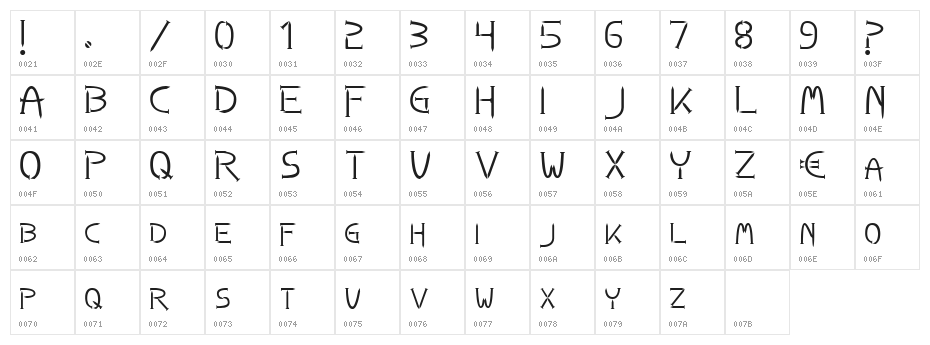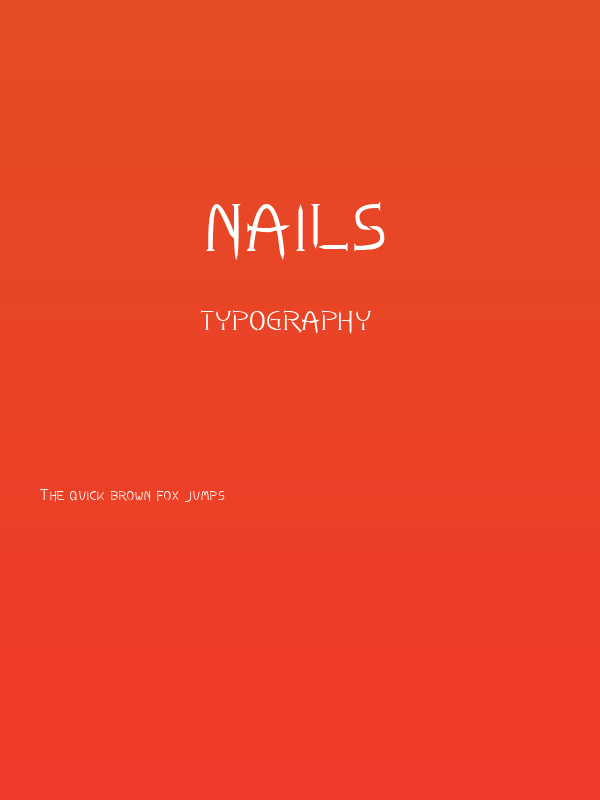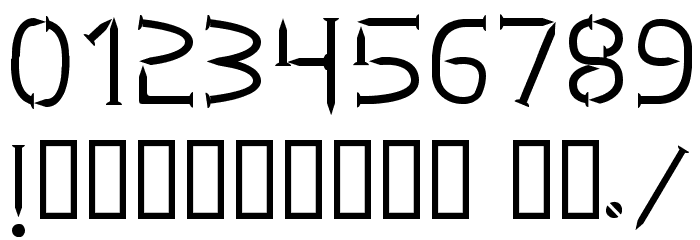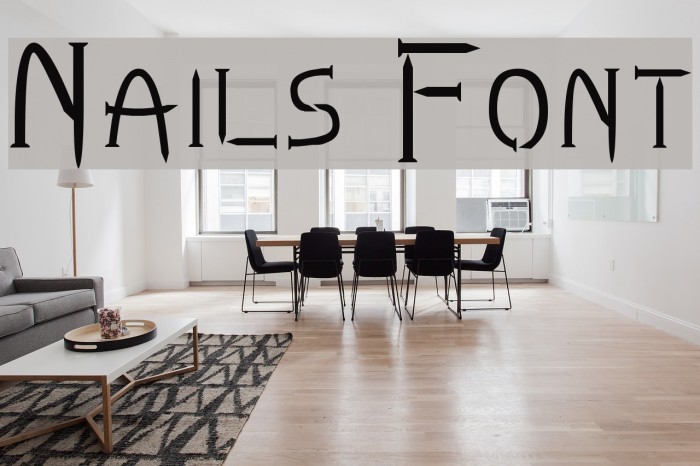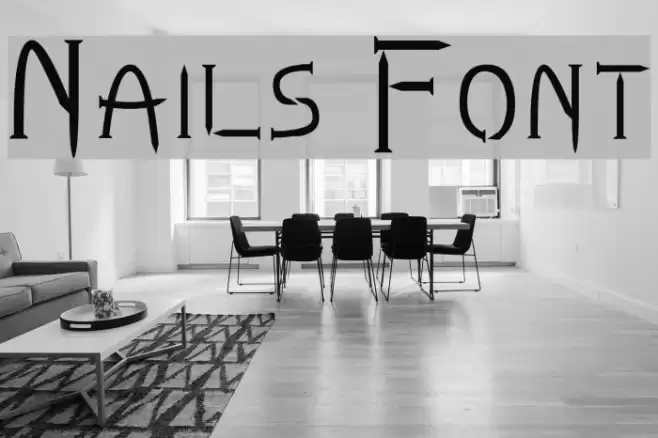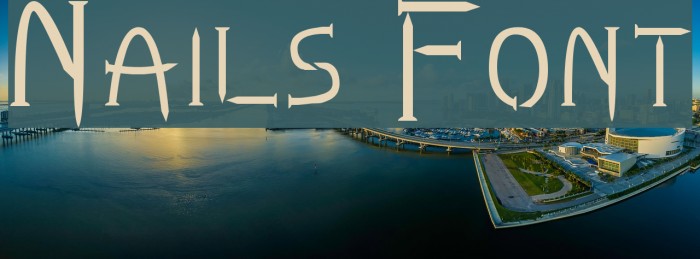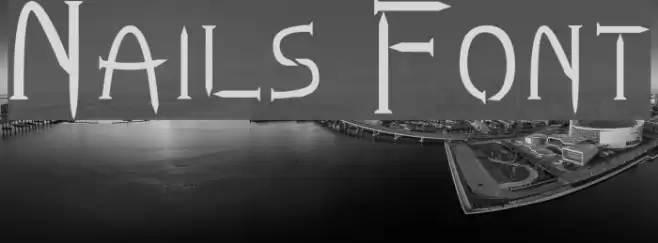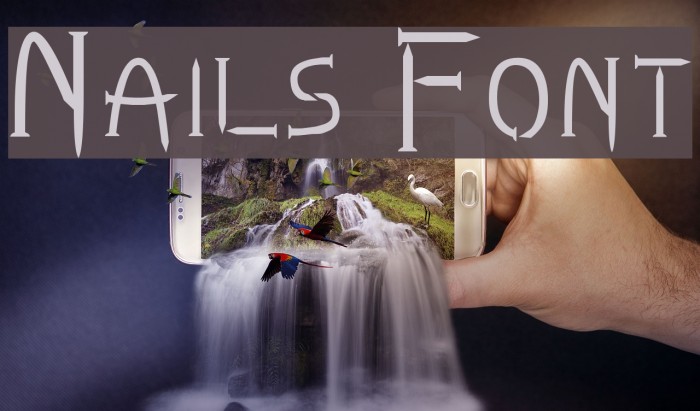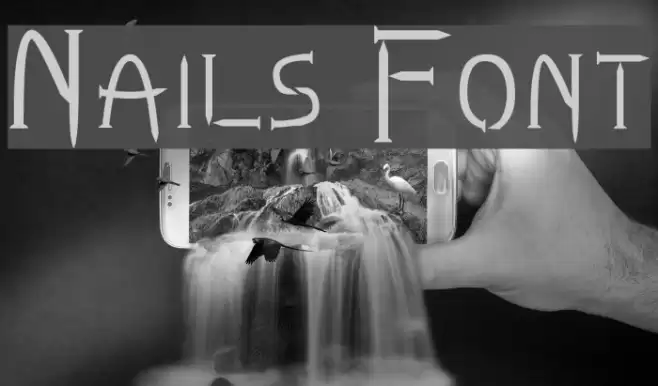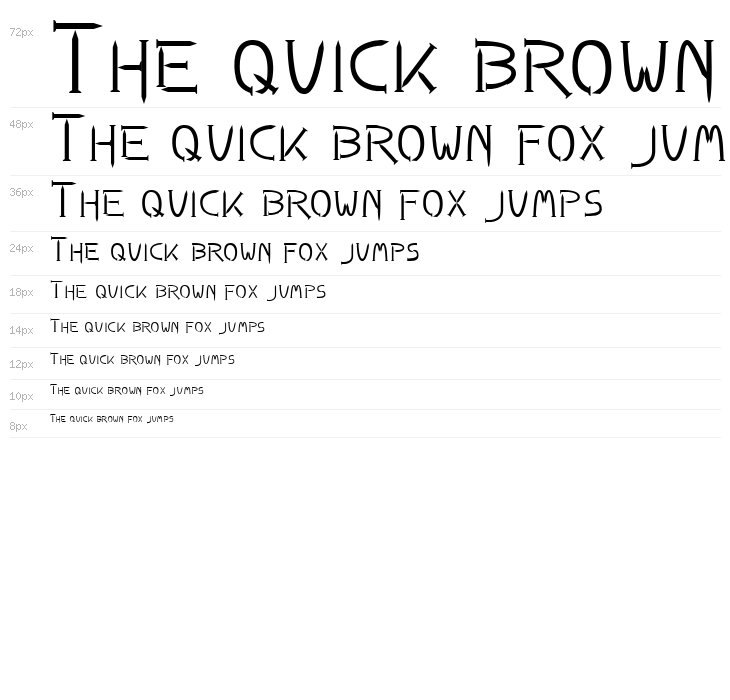
Nails Font
| Estilo geral | Modern, Industrial |
| Projetos propostos | Ideal for music album covers, posters, branding for edgy or modern products, and any design needing a bold, standout typeface. |